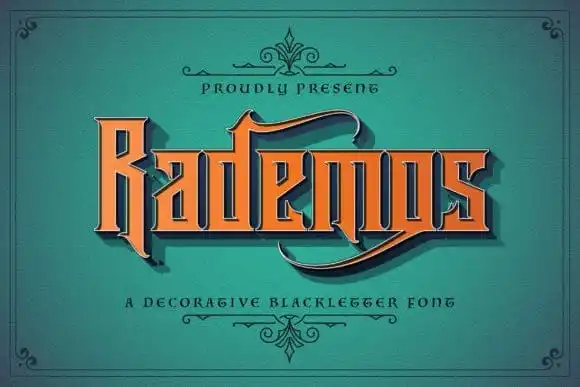
A Rademos Blackletter Font é uma criação única que combina a elegância clássica com os contornos modernos do Victoriano Moderno. Esta fonte é ideal para quem valoriza o equilíbrio entre a tradicional e a contemporânea, apresentando alternativas impressionantes que tornam seus textos ainda mais distintos. Desenvolvida pelo designer StringLabs no site de criação 99designs, ela representa uma verdadeira autenticidade na tipografia Blackletter, um estilo caracterizado por suas curvas arredondadas e detalhes elegantes. Com sua forma levemente arredondada, a Rademos Blackletter não apenas dá um aspecto moderno à fonte tradicional, mas também proporciona uma sensação de sofisticação clássica. Adicionar esta fonte aos seus projetos criativos é como dar uma nova vida ao seu design, tornando-o ainda mais chamativo e memorável. Ideal para aplicar em nomes comerciais, designs de logotipos ou qualquer projeto que exige um toque distintivo, a Rademos Blackletter Font é uma escolha certeira para aqueles buscando um equilíbrio entre o clássico e o moderno.